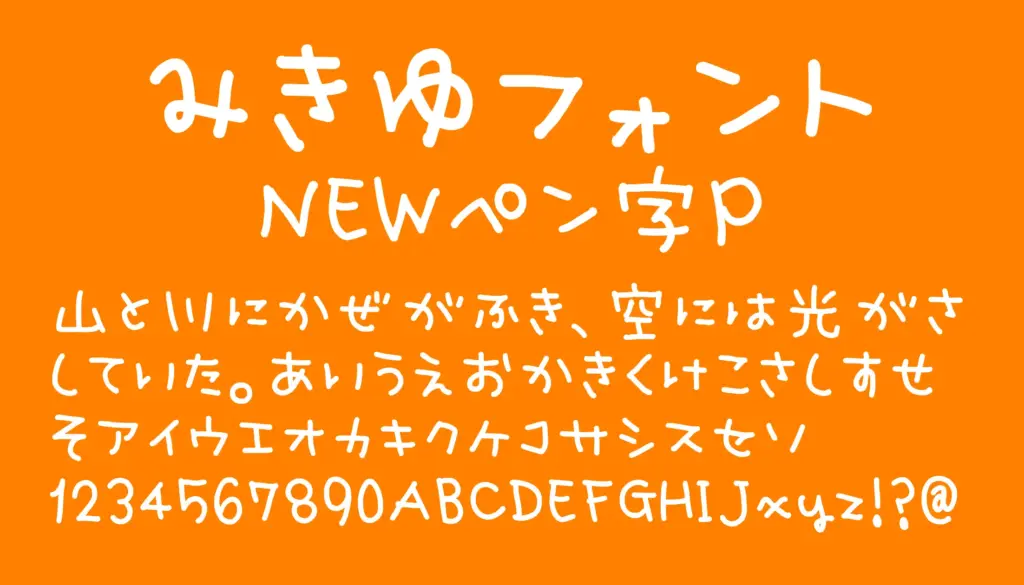
太めのペンで書いたような、やさしくてかわいい手書き風フォントです。元になった「ペン字P」よりも、ひらがなやカタカナ、アルファベットが少し小さくなり、漢字とのバランスがより自然になりました。日常的な文章はもちろん、子ども向けの印刷物や女性向けのデザイン、ブログ、チラシなどにもぴったり。やわらかい雰囲気を出したいときに、気軽に使えるフォントです。
みきゆフォント NEWペン字P